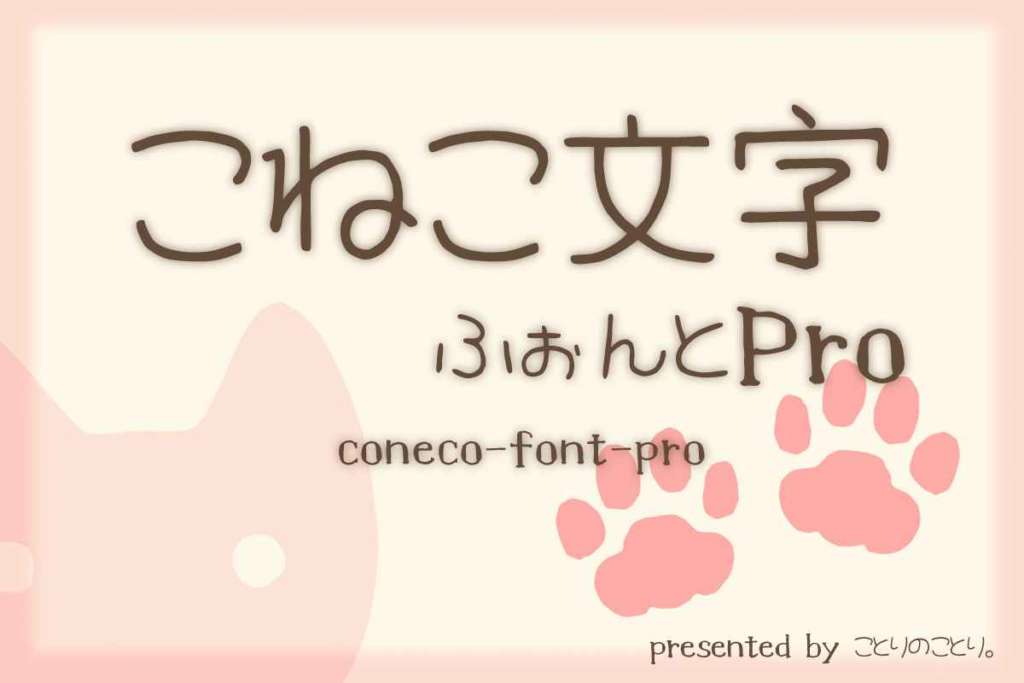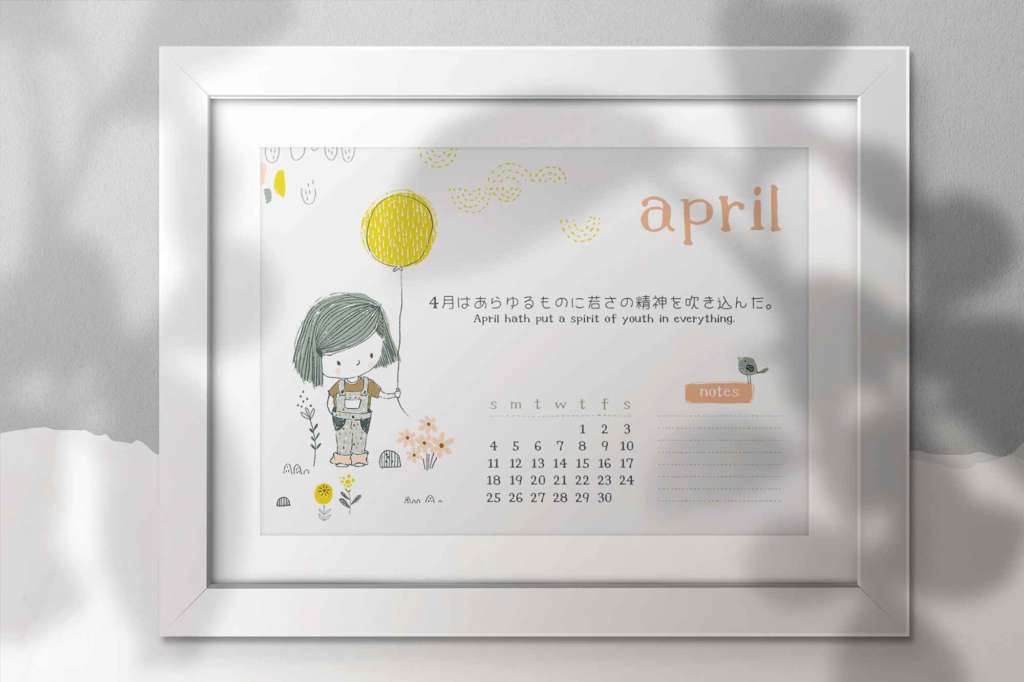
今回のバンドルは「揃えておきたい!ほっこり手書きフォント集」。漢字も使えるかわいい系の日本語手書きフォント3種セットです。メニューやチラシ、お知らせ、ポスター、年賀状、SNSの投稿画像など、幅広い用途に利用できます。
「揃えておきたい!ほっこり手書きフォント集」の気になる中身
ことり文字ふぉんとPRO
小鳥をイメージしたかわいらしい「ことり文字ふぉんとPRO」。ウェイトも2種類あり、用途に合わせて選べます。
- 2書体のことり文字ふぉんとPro (Regular/Light)
- 2書体のことり文字ふぉんとPro 等幅 (Regular/Light)
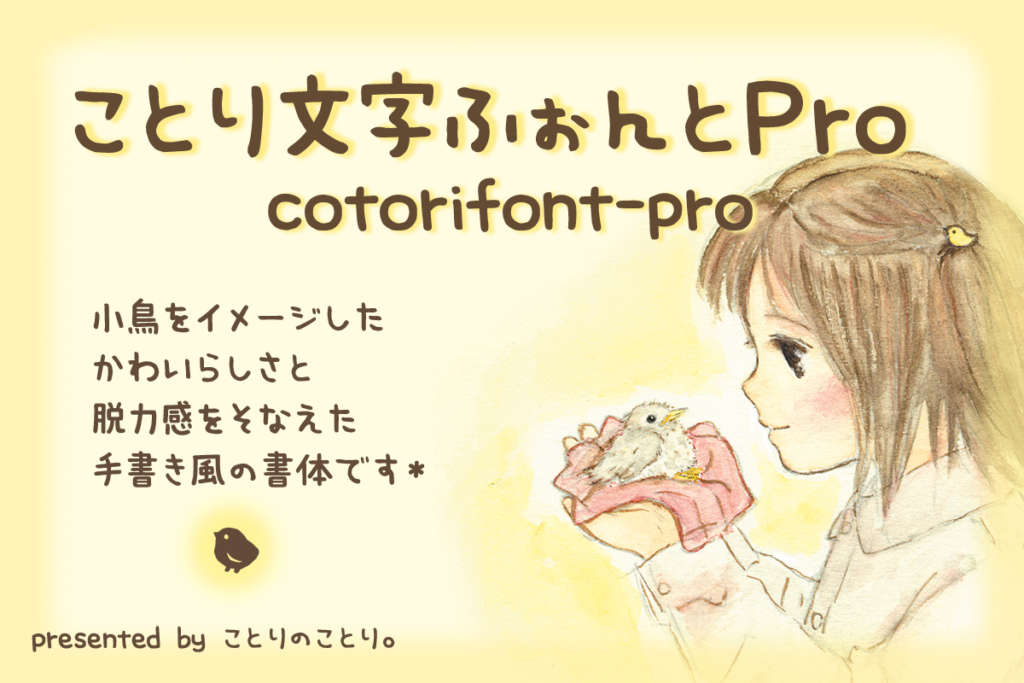
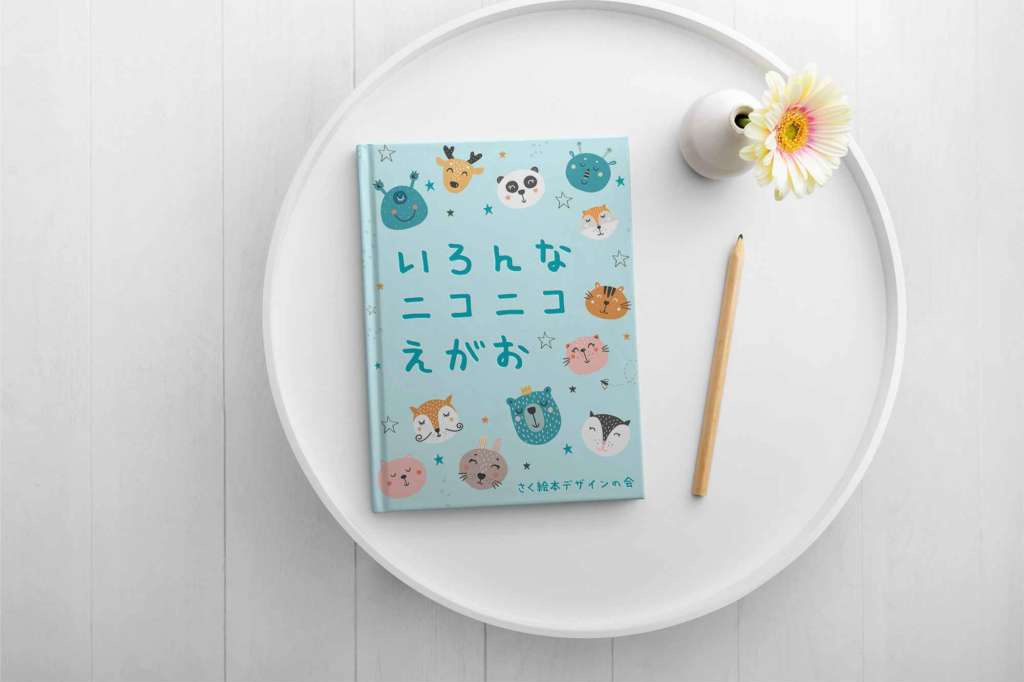
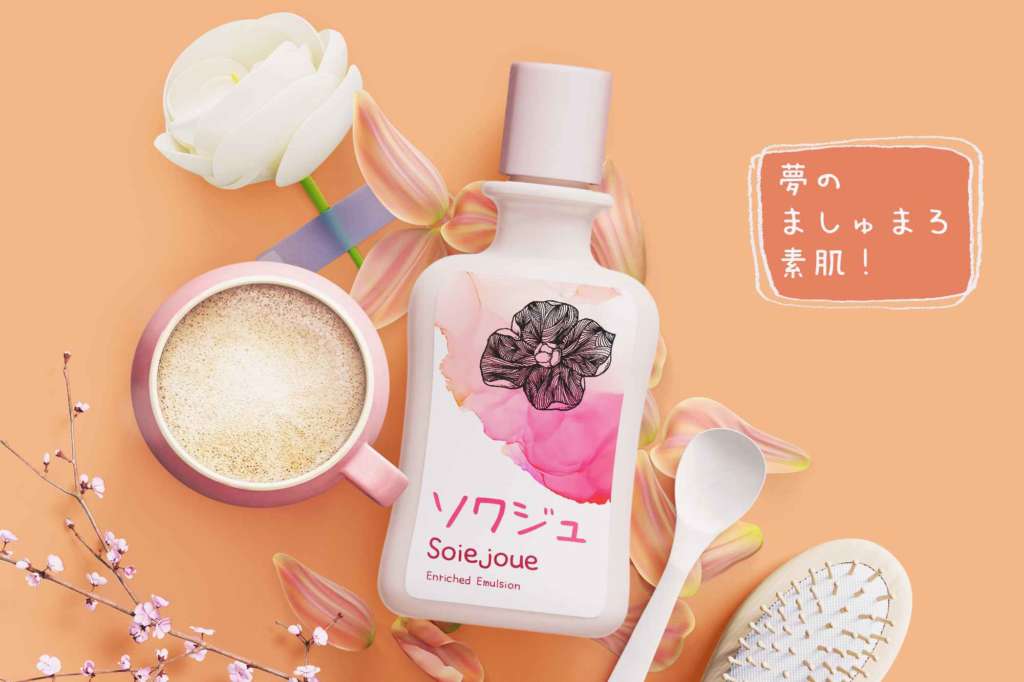
こうさぎフォントPRO
カフェのメニューや黒板の手書き文字からヒントを得た「こうさぎフォントPRO」。画数の多い漢字が並んでも、読みやすくやさしい印象が残せる実用的なフォントです。
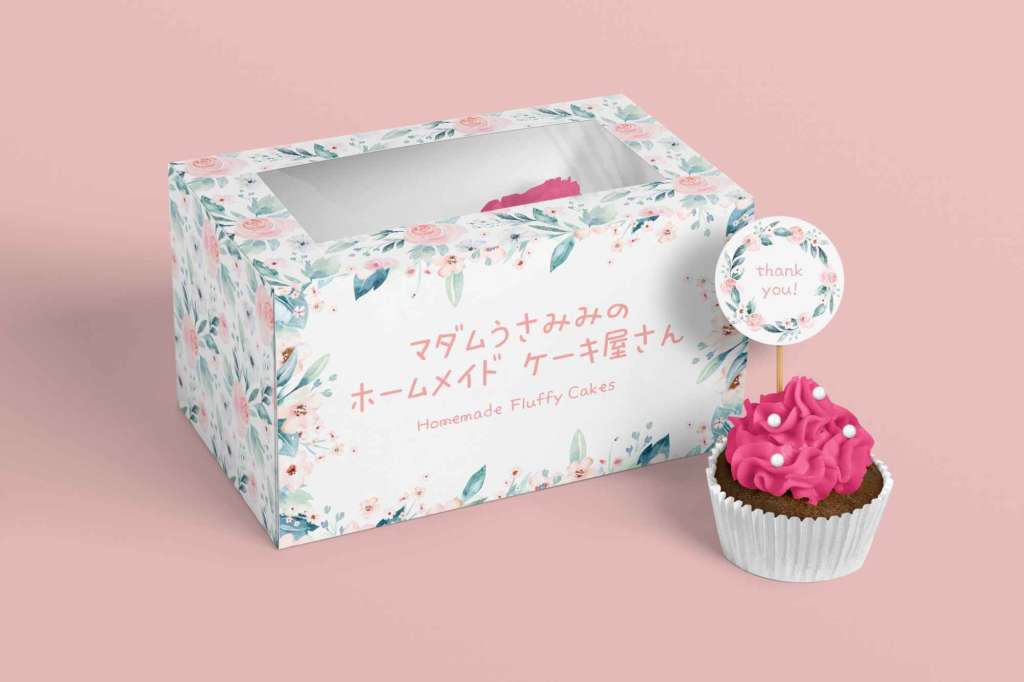
こねこ文字ふぉんとPRO
1970〜80年代ごろ流行した丸文字文化へのオマージュとしてつくられた「こねこ文字ふぉんとPRO」。ひらがなが多いテキストに使うのがオススメです。